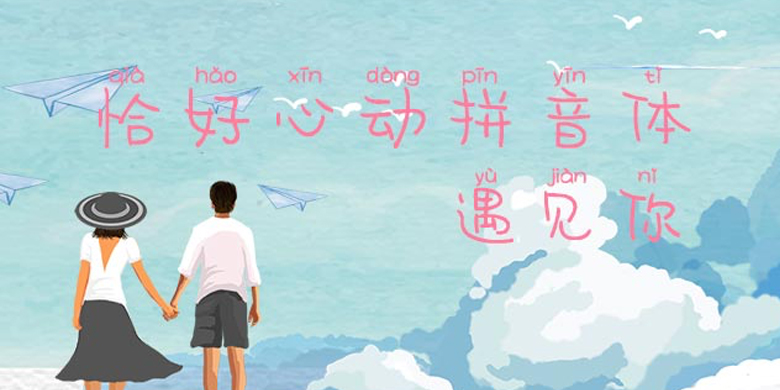
方正手迹-恰好心动拼音体
方正手迹-恰好心动拼音体,这款字体结构工整、笔画清晰,兼顾美观与易读性,适用于标题、正文、海报、包装、LOGO 等多种场景。字形优雅稳定,风格百搭耐看,适配日常排版与创意设计,让文字呈现更舒适、更具质感。方正手迹-恰好心动拼音体一笔一画,皆是细节,以均衡的比例、流畅的线条打造舒适视觉体验,字形端正大气,风格简约现代。无论是商业设计、品牌宣传还是日常排版,都能轻松驾驭,让文字更有格调与力量。方正手迹-恰好心动拼音体字体下载。
笔画简单,整体向下的趋势,显得可爱有趣,作为正文阅读,增添了趣味。适用于少儿类书刊,及现代诗歌、短文的排版以及文化、商业类品牌的广告语设计。